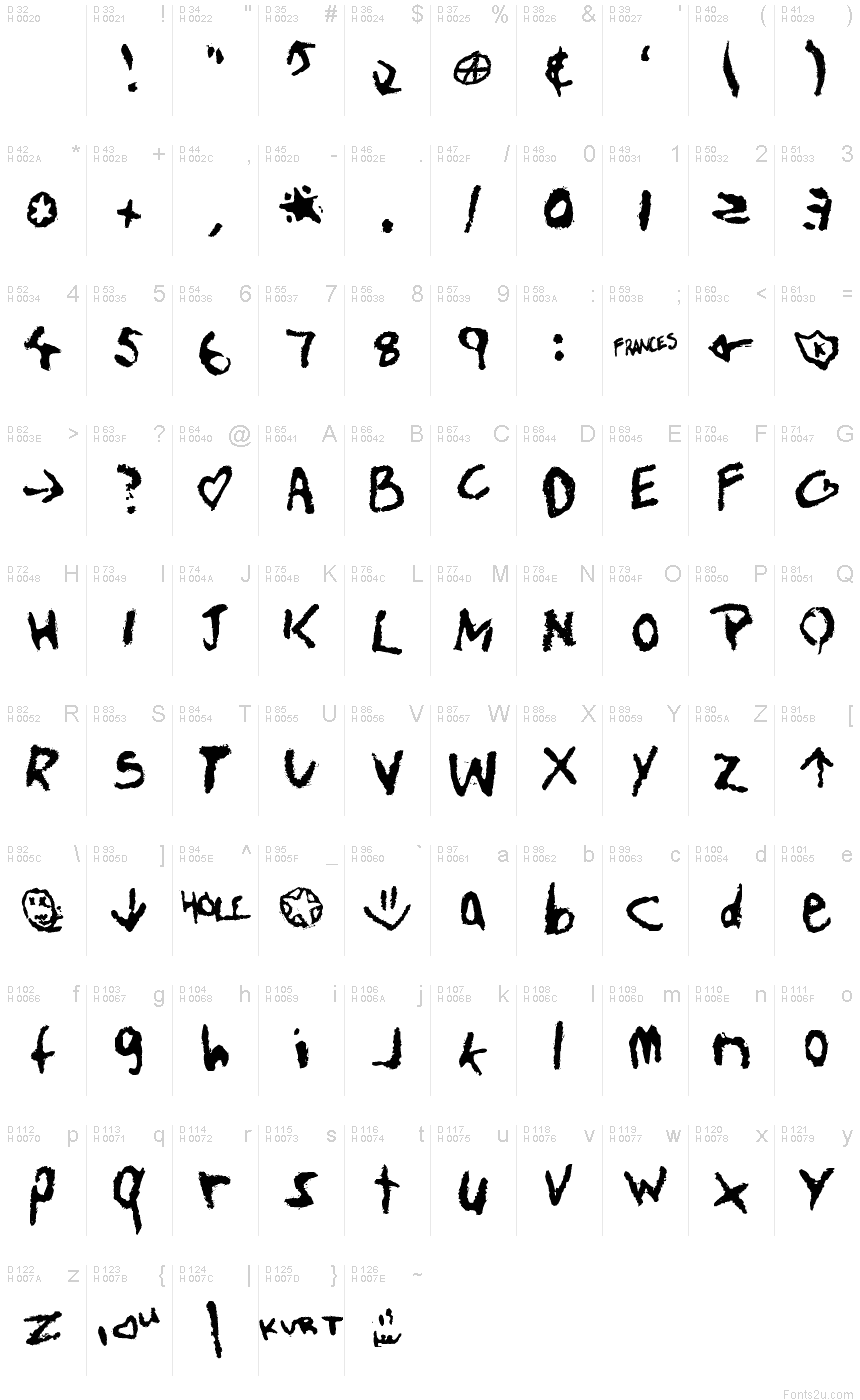
teen spirit
Teen Spirit autorstwa Stevena J. Lundeena to darmowy font grunge typu brush o surowym, „podrapanym” wyglądzie, który przywodzi na myśl punkowe ulotki i plakaty z koncertów w piwnicach. Litery są masywne i nieregularne, mają poszarpane krawędzie, wyżłobione ubytki i rytm malowania ręcznego, który nadaje teksturze głośny i niespokojny charakter.
Świetnie pasuje do opraw muzycznych, fanzinów, plakatów, grafik streetwearowych i nagłówków, gdzie zależy Ci na surowym, ręcznie wykonanym efekcie, a nie na wygładzonej formie. Jako darmowy font, sprawdza się również w tytułach i krótkich hasłach – jego szorstkie kształty pędzla niosą ze sobą wystarczająco dużo charakteru, nie potrzebując wiele miejsca.